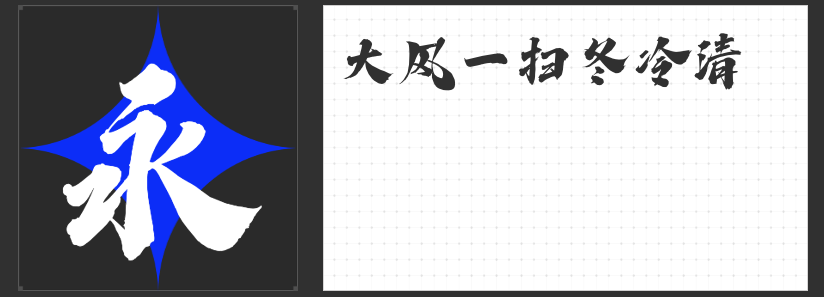
国潮江湖风字体美学指南:四款刚柔并济的东方视觉利器
当传统笔墨邂逅现代设计语言,国潮与江湖风格的视觉表达正突破次元壁,在品牌包装、影视海报、游戏界面等领域掀起文化新浪潮。本文精选四款兼具历史韵味与先锋气质的字体,以笔画为剑,结构为甲,为设计注入东方美学的当代生命力。
一、造字侠热辣隶简
这款突破传统隶书框架的创意字体,以扁宽中宫构建视觉张力,横笔如刀劈斧凿般开张对称,竖钩则以直线概括书写力量,形成刚柔并济的戏剧性对比。其撇捺收笔处的细粗过渡,既保留了汉隶的古朴韵味,又通过几何化处理赋予现代机械美感。在需要强调仪式感的场景中,这款字体能瞬间唤醒观者对青铜器铭文的集体记忆。
二、万人字造踏歌行体
结体方整如碑刻,用笔却暗藏行草意趣。斑驳的笔触模拟出岁月侵蚀的质感,方中带圆的转折处暗藏蓄势待发的力量感。这款字体最精妙之处在于对"飞白"效果的数字化再现——笔画边缘的虚实变化,恰似侠客衣袂翻飞时的残影,让静态文字产生动态叙事的可能。
三、造字侠灵霄简繁传神
取材自《西游记》天宫意象的硬笔字体,以瘦劲挺拔的笔画勾勒出凌空御剑的飘逸感。简繁双版本的设计兼顾实用性与艺术性,在保持书写流畅度的同时,通过笔画粗细的微妙变化,营造出"银钩铁画"的视觉韵律,特别适合需要营造神秘感的仙侠题材设计。
四、创客贴劲书体
这款毛笔字体的终极魅力在于"失控感"的精准把控——笔锋转折处的飞白如同侠客剑气外泄,收笔处的加重处理则似内力灌注。设计师巧妙保留了书写时的自然抖动,让每个字符都成为独一无二的艺术品,在需要传递豪迈气概的场景中具有压倒性表现力。
从庙堂之高到江湖之远,这四款字体以不同的方式解构东方美学基因。它们既是文化符号的载体,更是视觉语言的革新者,在保留汉字结构精髓的同时,通过现代设计手法拓展了传统书法的应用边界,为当代国潮设计提供了更具张力的表达工具。